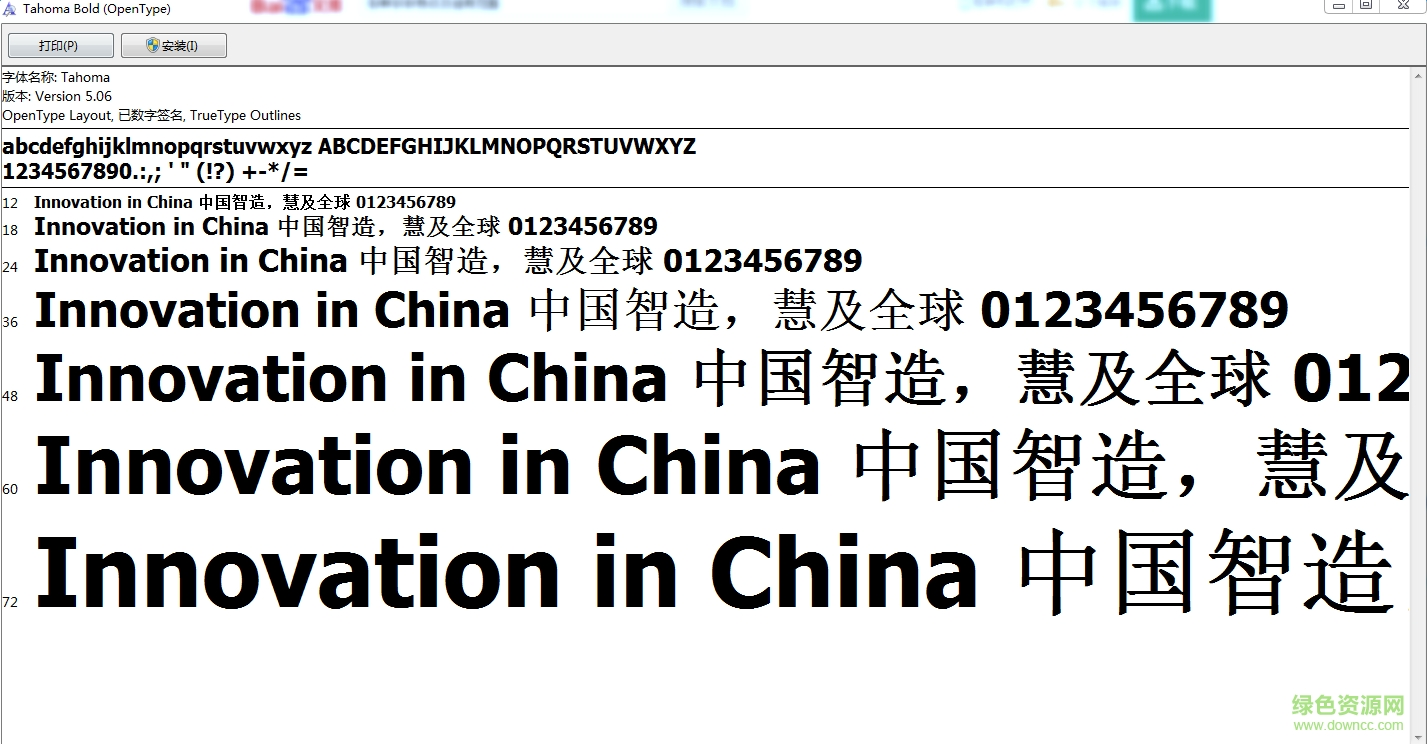
tahoma bold字體是一款字形飽滿的粗體字體,字體特點(diǎn)是粗黑醒目,可應(yīng)用于廣告、影視、印刷、宣傳等多個(gè)行業(yè),喜歡這款的小伙伴趕緊下載吧!
大河馬字體,Tahoma被采用為Windows 2000、Windows XP、Windows Server 2003及Sega游戲主機(jī)Dreamcast等系統(tǒng)的默認(rèn)字型。